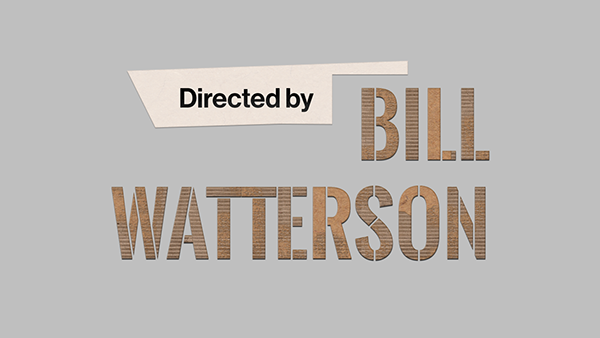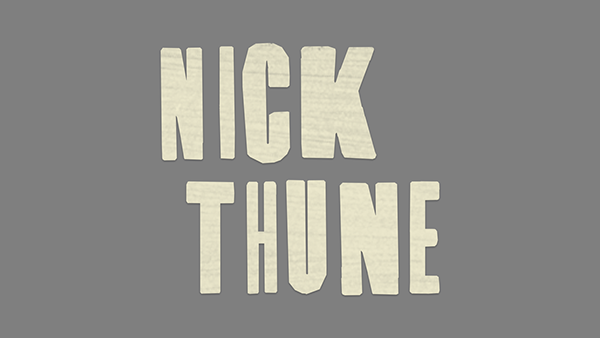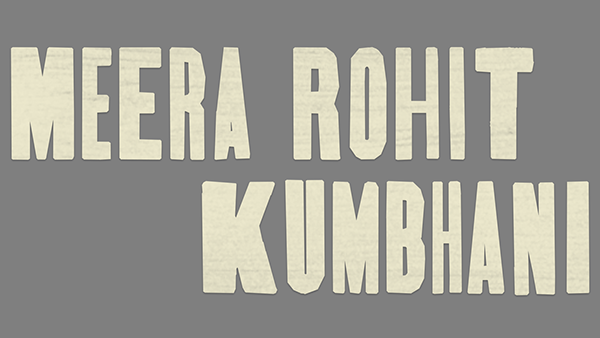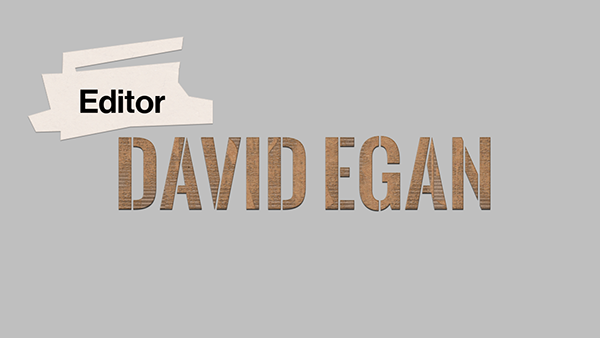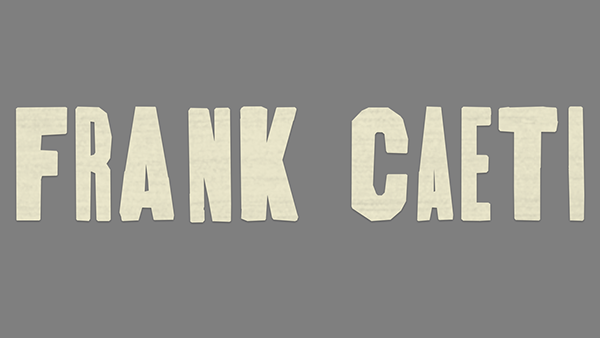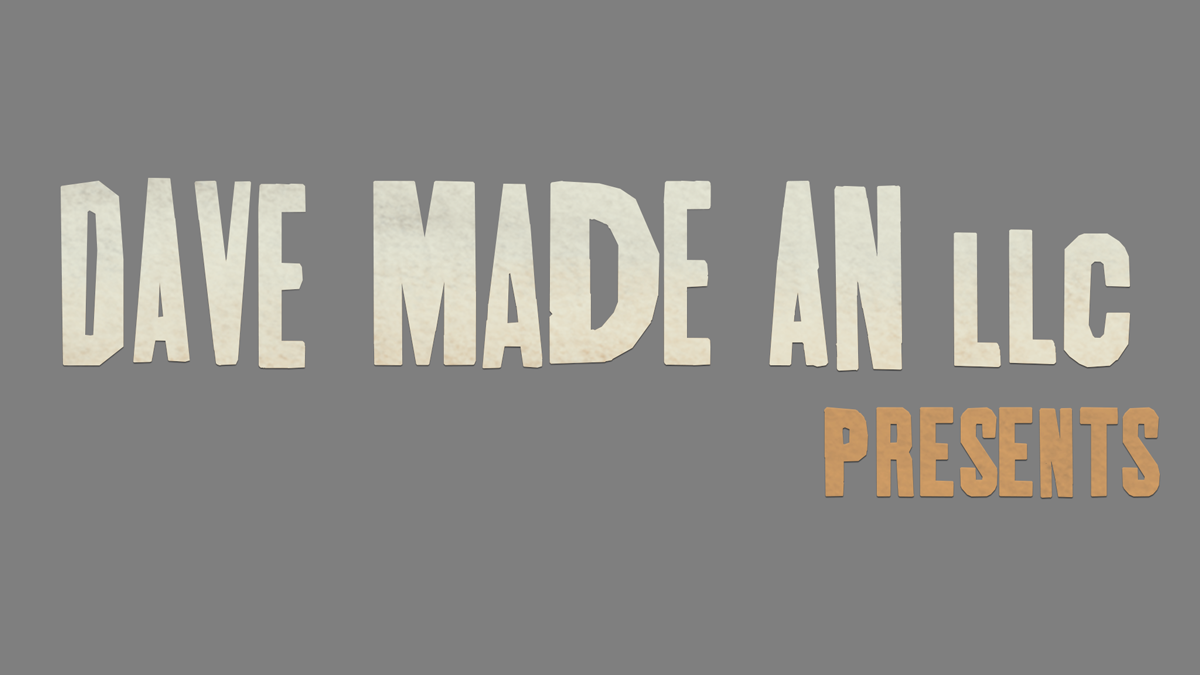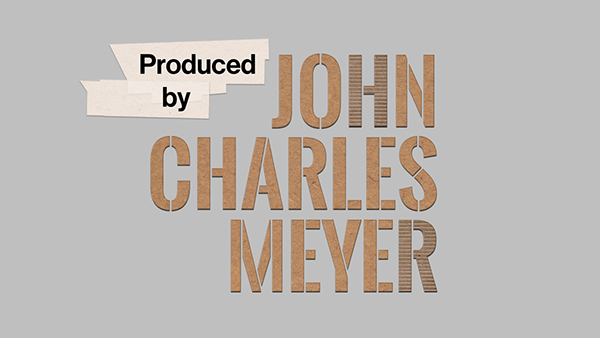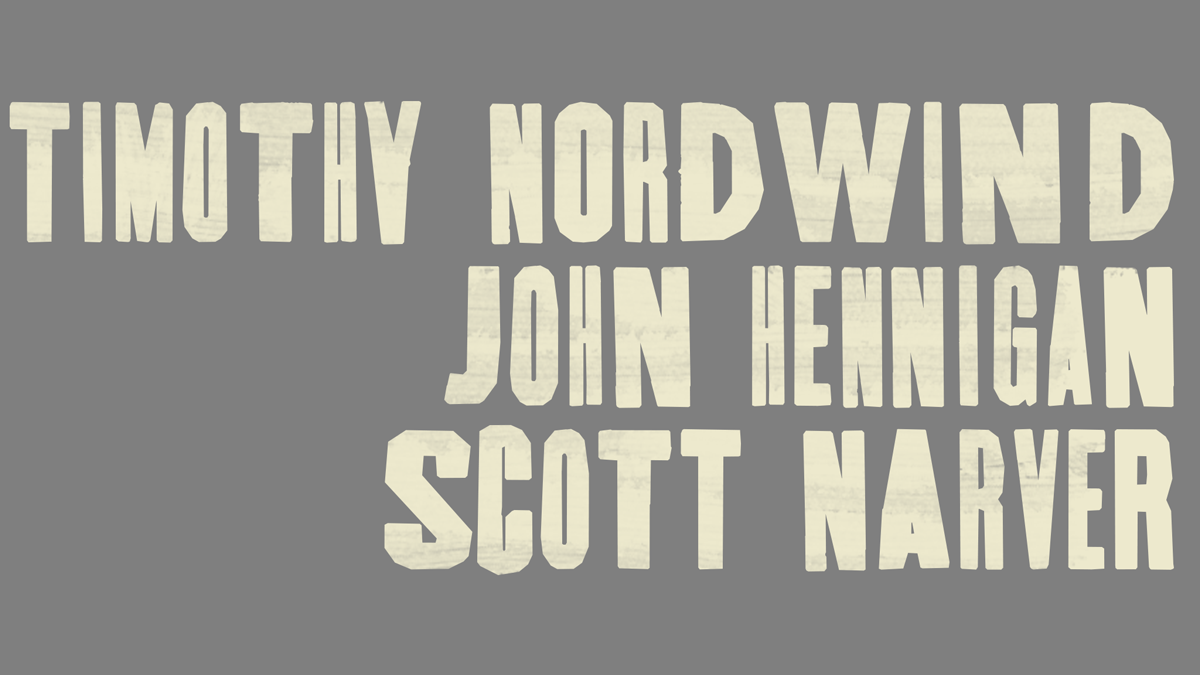
Los créditos iniciales y finales de esta maravillosa película fueron diseñados con piezas de papel recortadas (excepto los créditos finales), con tipografía que también funciona como etiquetas y magníficas animaciones de fondo de Kangmim Kim, Musa Brooker y Platypus Pictureworks.